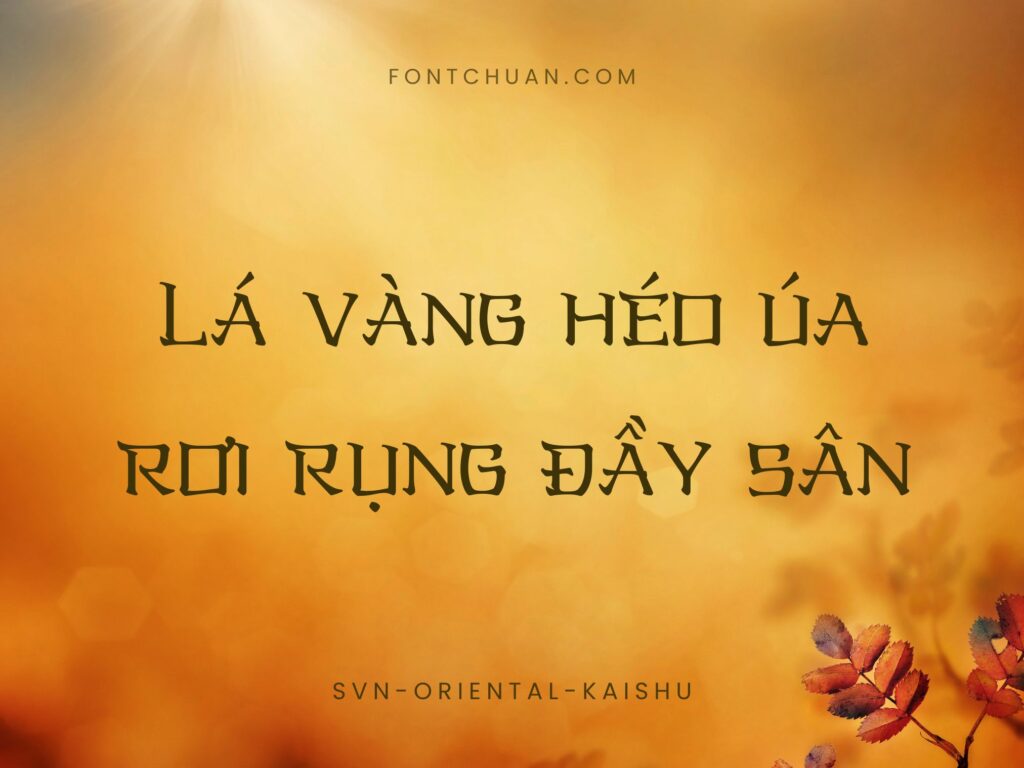
Font SVN Oriental Kaishu Style Nhật Bản Việt Hóa
Tác giả Font: Alexander Bobrov
Font SVN Oriental Kaishu là phiên bản Việt hóa của kiểu chữ Oriental Kaishu, được thực hiện bởi STYLEno.1 Fonts. Oriental Kaishu là một kiểu chữ thư pháp phương Đông cổ điển, được thiết kế bởi Alexander Bobrov và phát hành bởi Indian Summer Studio. Font này được tạo ra dựa trên nguyên tắc của thư pháp Kaishu truyền thống Trung Quốc (Kaisho trong tiếng Nhật) và các ký tự kana Nhật Bản, mang đến sự kết hợp hài hòa giữa nét đẹp truyền thống và hiện đại. Oriental Kaishu bao gồm đầy đủ các ký tự chữ hoa, chữ thường, chữ số và dấu câu, hỗ trợ đa ngôn ngữ, phù hợp cho nhiều mục đích sử dụng khác nhau như thiết kế logo, tiêu đề, bao bì sản phẩm và các ấn phẩm truyền thông.
SVN Oriental Kaishu lý tưởng cho các dự án thiết kế yêu cầu sự tinh tế và phong cách phương Đông, như thiết kế logo, tiêu đề, bao bì sản phẩm và các ấn phẩm truyền thông. Các ngành nghề như quảng cáo, giáo dục và bất động sản có thể tận dụng font này để tạo điểm nhấn trong thiết kế. Ngoài ra, font cũng thích hợp cho các sự kiện như Tết, Giáng sinh, Valentine và các lễ hội khác.